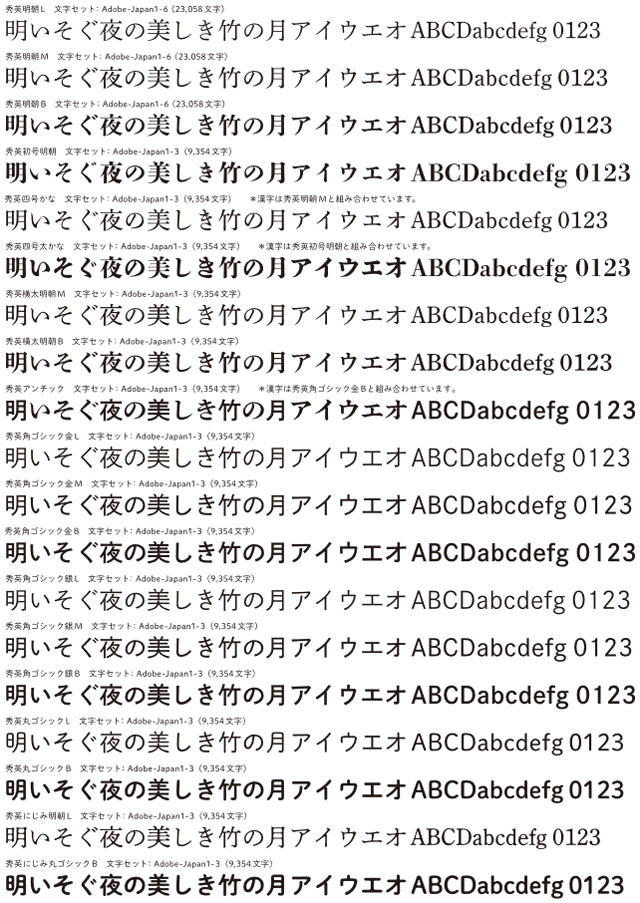
100年以上に渡り継承されているフォント「秀英体」を知っているか
知る人ぞ知る名フォント、「秀英体」を知っているだろうか。フォントに興味がない人でも、本好きな人であれば恐らく日常的に目にしているのではないかというフォントだ。
大日本印刷株式会社(DNP)で印刷されている本の本文には多く使われているし、あの日本語国語辞典「広辞苑」にも秀英体が使われている。
フォントには少しばかりの興味があった私だが、今回秀英体のフォント開発という珍しい職種のおふたりに話を聞いてきた。
DNP前で記念写真を撮ったら都心の会社とは思えぬ緑豊かさで合成っぽくなった
今回の舞台は秀英体の開発を行っているDNPだ。編集部からはフォントに関しては初心者という橋田さんと、動画編集作業でフォントはいじるものの、「スクロールから適当に選んでいます」という藤原さんが同行してくれた。
我々を出迎えて下さったのは、DNPで秀英体開発グループに所属する宮田さん(左)とリーダーの伊藤さん(右)。伊藤さんの持っている「原図」という“活字を作るための下書き”は1950年代前後の日付が書き込まれたとても古いものだ。デジタルフォントの今でも開発時には参考にしているのだそう。フォントガチ勢のような写りだが、実際に“フォントガチ勢”なのだ。
関西出身の伊藤さんは小学生の時、阪神のスコアボードが明朝体でかっこいいと思い、家のワープロで「掛布」や「バース」などと打っては「甲子園球場っぽい!」と楽しんでいた子供だったという。一方で宮田さんも、小学校のクラブ活動でレタリングクラブを選択している。ふたりとも、小学校時代からフォントに親しんでいたのだ。
今回はそんなフォントが好きで仕事にしているおふたりに秀英体について、そして全く見当がつかない「フォント開発」という職業について聞いてきた。
秀英体とは
秀英体
DNPで開発している「秀英体」とは、豊富なファミリーを持つ書体の総称。主軸となる「秀英明朝」は、本文用の明朝体として長く書籍や雑誌に使われてきた。
秀英体の歴史は古く、DNPの前身である秀英舎が創業したのは明治初期。
その頃からフォント開発を続けている秀英体、現在までに100年以上に渡って継承している書体なのだ。フォントって勝手なイメージで、パソコンが一般家庭に普及しだした2000年前後からなのかと思っていたので意外な歴史の古さに驚いた。
……と言っても、「秀英明朝」がどんなフォントかどうか、ピンと来ない人も多いだろう。まずはこれを見てほしい。
こちらは宮田さんが今回の取材のために(!)作ってくれた「ふぉんと視力表」だ。この中には秀英明朝をはじめ、MS明朝、ヒラギノ明朝、源ノ明朝、リュウミンの5種類のフォントが使われている。
一列目の一見同じに見える「い」だが、すべて違うフォントが使われている。このなかから秀英明朝を見つけることができるだろうか。
早速正解に移らせてもらうが、こちらの「い」の一筆書きが特徴的なフォントが秀英明朝だ。「い」以外にも「こ」や「に」などに一筆書きっぽい“秀英っぽさ”が表れる。秀英体は比較的見分けやすいフォントなのだ。(ちなみにこの記事のタイトルも実は秀英明朝である。)
※編集部注:タイトルが秀英体明朝なのはパソコンで見ていている方のみです
芥川龍之介/三つの宝より。こちらにはフォントではなく、活字(秀英四号)が使われている
活版印刷の時代から、時代に合わせて形を変えつつ継承されてきた秀英体。かなり昔の本にも使われているので古本屋で思わぬ出合いがあったりする。秀英体がわかると、古本屋に行くのももっと楽しくなる。
秀英体ラインアップ
とはいえ秀英体にはいろいろな種類があり、丸ゴシックや角ゴシックなどは「い」の間はつながっていないし、秀英体シリーズのすべてが一筆書きっぽいフォントなわけではない。しかし、いずれも秀英体の持つ古典的で上品さをどこか感じるフォントになっている。
こんなに素敵なフォントなのに「秀英体」の存在を最近まで知らなかった。実はその背景には、秀英体が「門外不出のフォント」と呼ばれた歴史があったのだ。
「門外不出のフォント」だった秀英体
井口:秀英体というフォントがそんなに長く続いているフォントだということにも驚きました。恥ずかしながら秀英体を知ったのは最近だったのですが、レトロでかわいい書体ですね。
宮田:それもそうかもしれませんね。というのも、秀英体って「自社で印刷する時の書体」としてスタートしたので。明治の頃は活字販売もしていましたが、その後はほとんど外に出してないフォントだったんです。
井口:そうだったんですか! じゃあいろいろと使われるようになったのも最近ですか?
宮田:オープン化してから利用事例が増えて、身近になってきたっていうのはここ数年のことですね。
かつては「門外不出の書体」だった……!
伊藤:秀英体は長らく「門外不出のフォント」と言われていました。書籍を組版するところの工場にしかなかったので、ポスターやパッケージにはそもそも使いようがなかった。
今でこそロゴや商品のパッケージにも使われるようになりましたが、かつてはお菓子のパッケージに使われることはなかったんですよ。
井口:オープン化されて反応がダイレクトにわかるというか、コンビニや本屋さんで自分の開発した書体と出会えるようになったわけですよね。それってやっぱり嬉しいものですか?
伊藤:それは、めちゃくちゃ……嬉しいですね……!
微笑む伊藤さん
井口:やっぱり! ご自身で開発された書体の使われた商品、買っちゃったりします?
伊藤:買います。ジャケ買いというか、フォント買いします。お菓子とかもみんな秀英体のお菓子買ってきますし。それはいいところかな。フォントなのでどこにも使えるんですよね。
井口:やっぱり買っちゃうんですね!
伊藤:自分の作ったフォントがミュージシャンのポスターとかに使われていると、自分は全然関係ないのに一緒にやったかのような気持ちになる。僕はイチロー好きなので、ムック本の表紙に使われていた時は震えました。イチローの引退を一緒に飾った気持ちになったりして。
井口:フォント開発する人ならではの感情でしょうね……!
宮田:約4万人いるDNP社員はフォントに関わっていない人も多いので、社内で秀英体を知っている人もそんなに多いわけではないんです。でも10年前と比べたら社内の認知度も増えましたね。オープン化する前は秀英体を知っていても、自分のパソコンでは使えないフォントだったのであまり実感がなかったんですよね。
井口:秀英体、歴史は古いけど書籍以外で一般に出回りだしたのは最近なんですね。これから見かける機会は増えていきそうです。コンビニとかで注目してみないと。
フォントを作るのは超大変
フォント開発者ならではな開発の喜びなどを聞いた。では、フォントを開発する苦労はどうなんだろう。たくさんのフォントを作る作業は想像しただけで大変そうだが……。
伊藤:フォントを作るのはご想像通り大変で……。ちなみに、一書体で何文字ぐらい作ると思いますか。
井口:英語だとアルファベットだけだけど日本語はひらがな、カタカナ、漢字とあるので想像つかないですね……8000字とかですかねえ。
伊藤:はじめは7000字位だったんですけど、今は一書体で2万3000字位は作っています。
秀英体は平成の大改刻プロジェクト(2005~2012年)で7年かけ、大規模なリニューアルを行った
井口:2万3000字!? それを何人くらいで作っているのですか?
伊藤:中心となったのは自分と宮田とあともう1人で3人でした。でも3人だけではなく大きなプロジェクトとして、いろんなフォントデザイナーの方たちとプロジェクトを組んでやっています。だから100人はいなくても、何十人は関わっていますね。
井口:DNPの3人が中心となって……。そして、世の中にはフォントデザイナーという職業の方がいるんですね。
伊藤:我々がフォントの設計をして、それに合わせて字を作ってもらって。手書きじゃなくてベジェのillustratorのデータみたいなもので。
宮田:線の引き方がillustratorみたいな、フォント開発専用のエディタがあるんです。でも例えばひらがなは文字を書いて、スキャンして、アウトラインを取っていく方が綺麗にできるんです。
伊藤:大事な字は手で書いてるんですよ。あとはフォントの作り方にもルールがあって、ここの角度はどれくらいとか。そういうフォントの設計書があるんですけど。
井口:そういうものがないとぶれて行っちゃうってことですよね。
伊藤:それで何十人で作っていく。見ていただくと分かる通り、縦画も実はまっすぐじゃないんです。下にいくにしたがって少し角度をつけています。
元の活字をスキャンして、当時の職人がどのように作っていたかを研究し、デジタルではこう表現しようと。そんな感じで縦画一本にもこだわっているので、払いはもっと難しいですね。そうしてチェックするのが我々。
宮田:これはコメント書く用のシートですね。実際は中を塗りにしたものでチェックしています。具体的な指示を出す時にこれを使います。
伊藤:そんな感じで7年かかりました。
井口:ヒィー!!!!
宮田:といっても書体数が多いので。10書体を作っているので、一書体で7年かかったわけではないです。明朝体は2万字作っていて、他のは1万字くらいです。全部で14万字ですね。
井口:作る数は書体でも変わってくるんですね!
宮田:本文用で使うとなるとカバーできるように多くの文字が必要……となると結果2万3000字とかなるんですけど、そうじゃないものはJIS第1・第2水準の約7000字あればカバーできるんです。
宮田:フォントには日本工業規格が定めた「JIS規格」という規格があるんですが、「JIS規格」を満たしているとユーザーさんに汎用的に使っていただけます。漢字はちなみにどういう順番で作っているかと言うと、こちら。
これがフォントを作る際に基本として優先的に作られる漢字……!
宮田:基本になる文字を先に作って、徐々に400字、10,000字と増やしていきます。
井口:こちらの21文字が選ばれている理由はなんですか?
宮田:「国」、「東」、「永」は基本となるパーツが入っています。お習字でも「永」の字は、はね、左払い、右払い、点、縦画などが全て入っているので練習するのにぴったりなんです。
井口:「永」の字をそういう観点で見たことなかったですー! あと、「鬱」という文字が入っているのが個人的に違和感あるのですがこちらは何故?
宮田:「鬱」は画数が多い文字ということで入っています。「鷹」や「酬」は、縦画と横画が多い漢字として印刷で潰れないかなどを見ます。
井口:それぞれの漢字に役割があるんですね。
伊藤:日本の「日」の字は、一番単純な文字をどれくらいの大きさで作るかというのがあるんです。書体によっては、「日」が大きかったり小さかったりします。
宮田:「三」は画数の少ない文字でバランスを見るためですね。
いったん広告です
VS絶対フォント感
取材の最後に、絶対フォント感を持つ伊藤さんに対し、私と藤原さんで「フォントかるた」に挑んだ。
19.jpg
フォントかるた
「フォントかるた」というのはフォントかるた制作チームが作っている、書体で見分けて札を取りあうかるただ。
20.jpg
伊藤さんは「こういうものがあるんですよ」と紹介してくれた際に「これはナールDB、筑紫A丸ゴシック……」と次々とフォントを当てていた。
そんな絶対フォント感の恐ろしさを目の当たりにしていたので、伊藤さんにはハンデを設定してもらった。
伊藤さんのハンデ
・かるたを上下逆側から取る(見にくい)
・フォント名の読みあげのみで取る(私たちは読み札も見せてもらった)
・5秒後にスタート
かなりハンデを設定してもらったがそれでも自分たちが伊藤さん相手になるとは到底思えない……。
21.jpg
フォントかるたは白熱した
こちらはフォントかるたを取っている光景ですが、それぞれの立ち位置とポーズに若干の西洋の宗教画っぽさを感じる絵になった(私がそう思っているだけかもしれない)。たぶん伊藤さんがフォント神の啓示(お告げ)を受けている。
結果は伊藤さんが3、藤原さんが3、自分が4と接戦だった。やったー! フォントかるたをやってみたら、もっと自分のフォント感を鍛えてみたいと思った。絶対フォント感は自分でも鍛えることができるらしい。伊藤さんがハンデが無い状態だったら……というのは考えるだけで恐ろしい。
専門的な話は面白いです
フォントの開発についての話は興味深かった。フォントかるたについても、自分には1枚も取れないのではないかと思っていたが実際やってみると取れたし、面白かった。フォントかるた、なにか既視感を感じていたのだが多分サイゼリヤの間違い探しだ。サイゼリヤの間違い探しが好きな人はフォントかるたもきっと楽しめるんじゃないかと思う。
秀英体スタンプ&秀英体でデコ文字
歴史のある秀英体だが、最近ではLINEスタンプや絵文字といった新しい分野にも挑戦しているそうだ。秀英体は書籍の表紙や帯、映画のポスター、お菓子のパッケージなどいろんなところで見ることができるので探してみてください。見分けるポイントは、「ひらがな」だ!